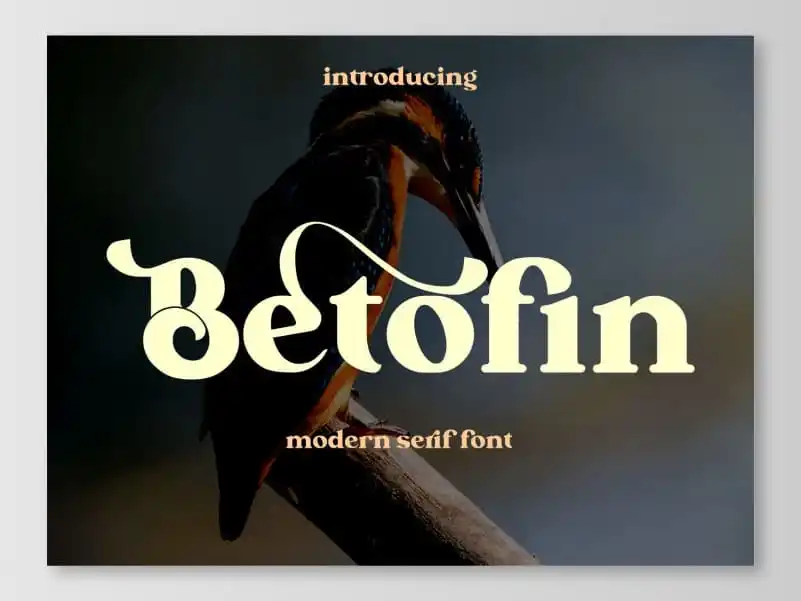
A Betofin Serif Font é uma elegante escolha para quem busca expressar um design sóbrio e cuidadosamente meticuloso. Seu traço serifado permite que se adapte com facilidade a inúmeras tarefas, seja ela um projeto gráfico de marketing digital ou uma revista de arte retro. Composta por linhas resistentes, essa fonte é perfeita para quem deseja dar destaque às ideias criativas, garantindo um toque único que torna seus trabalhos ainda mais atraentes e memoráveis. Escolha Betofin Serif Font como sua nova companheira de trabalho e veja o impacto inegável em seu design.